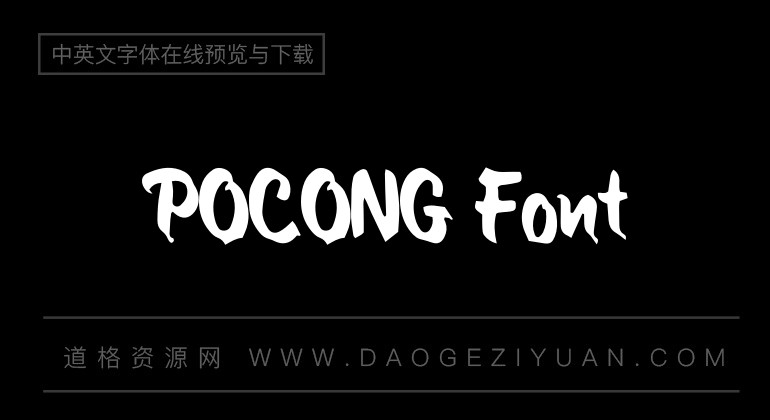
POCONG Font
POCONG Font是一种特殊的字体,它的外观像是一种传统的印尼鬼魂称为“Pocong”所穿着的白色裹尸布。这种字体的设计者是一个来自印度尼西亚的设计师 Ahmad Ramzi Fahruddin,他在2013年创建了这种字体。 POCONG Font的字母形状具有非常独特的特征,它们似乎被裹在一层厚厚的白色绸缎之中,这使得这种字体看起来非常的神秘和诡异。这种字体适用于一些特殊场合的设计,例如万圣节、恐怖电影、惊悚小说等等。 POCONG Font目前已经成为一种非常流行的字体,它在印度尼西亚的设计界和文化圈中拥有很高的知名度和影响力。
POCONG Font是一款非常不错的手写艺术字体,具有很好的视觉感,适合于文化类的宣传设计、商业类品牌的广告和产品包装设计以及个性化文字排版等较多场景。